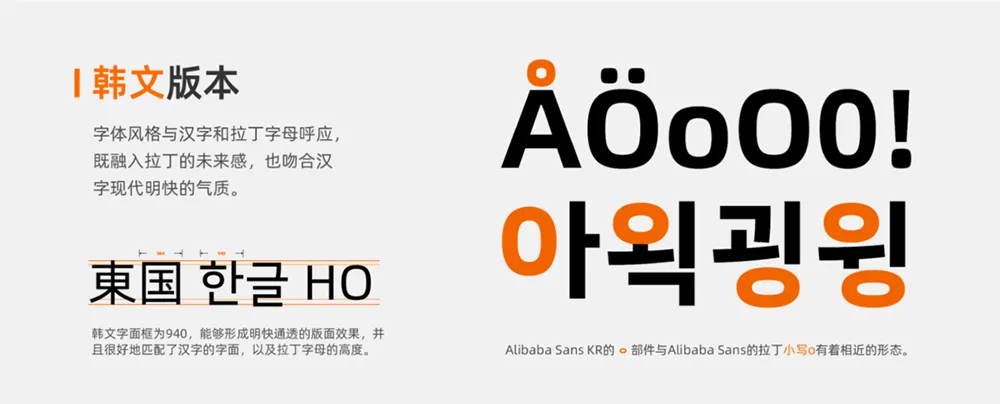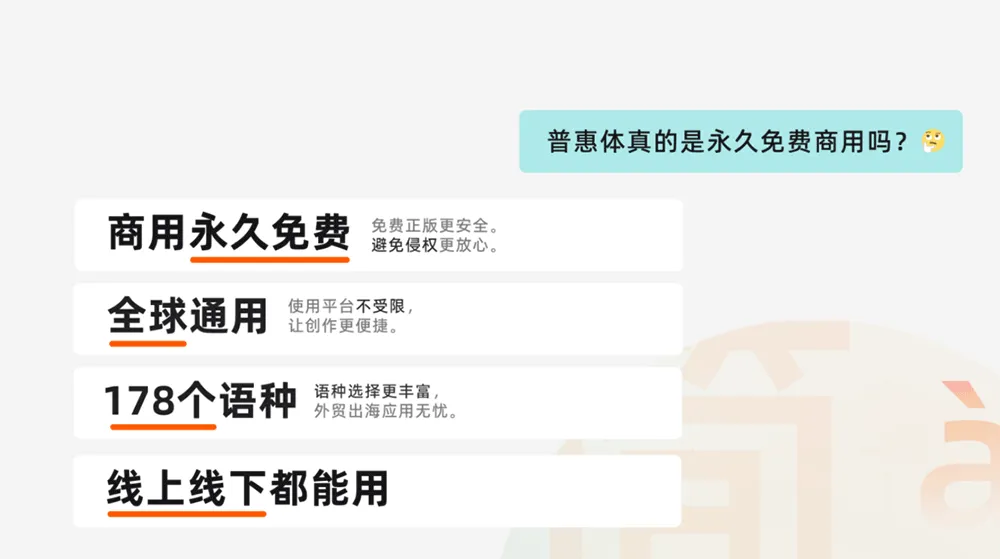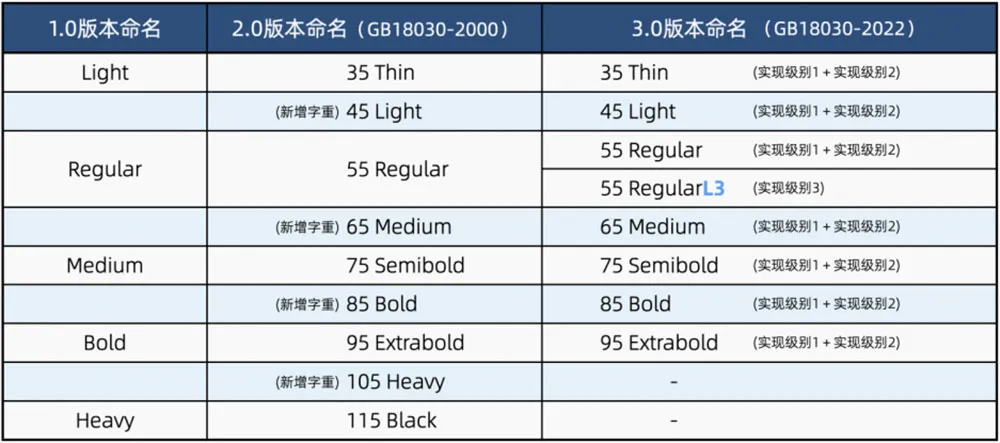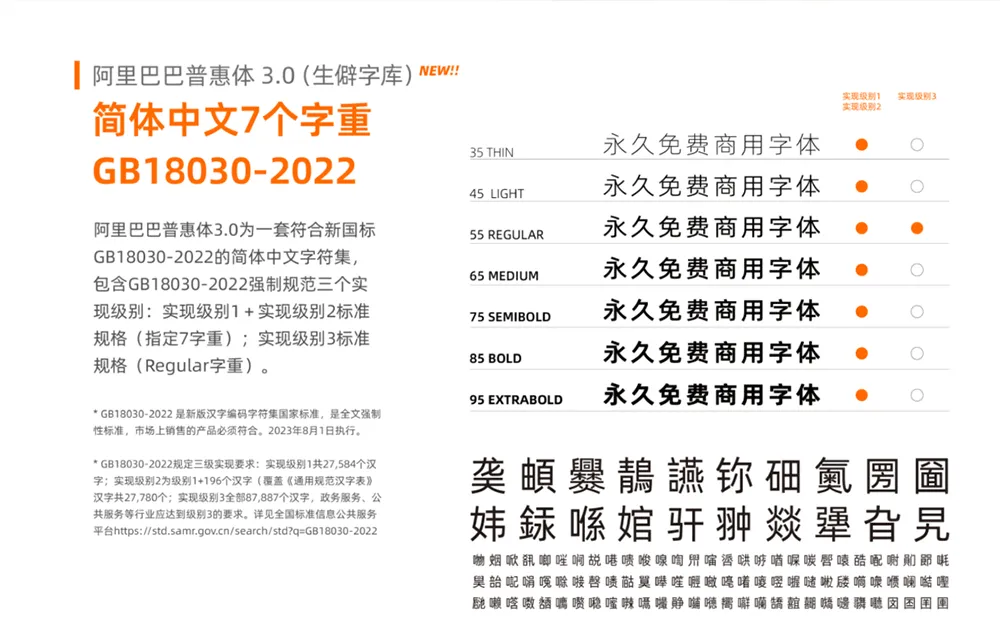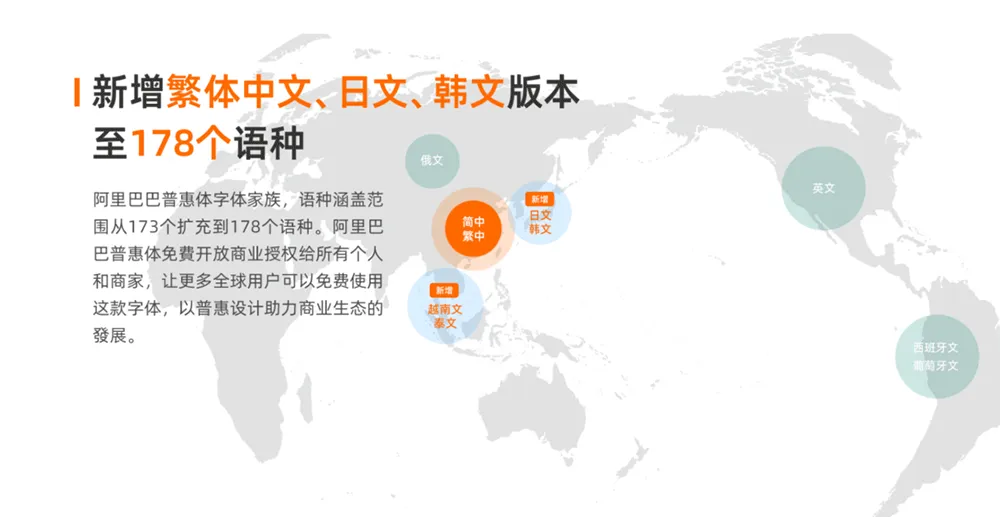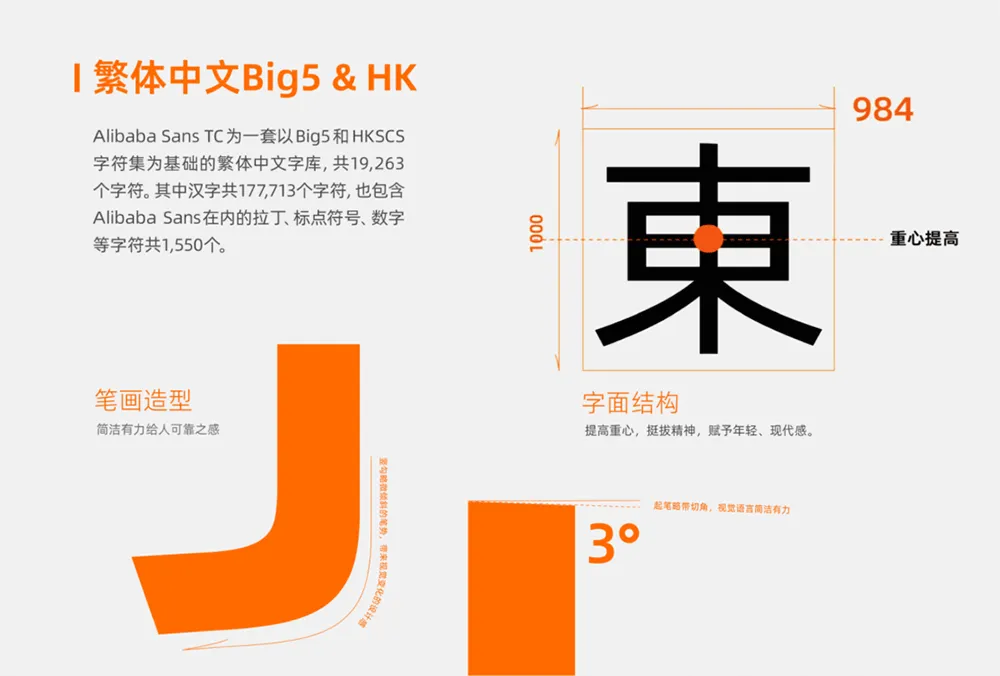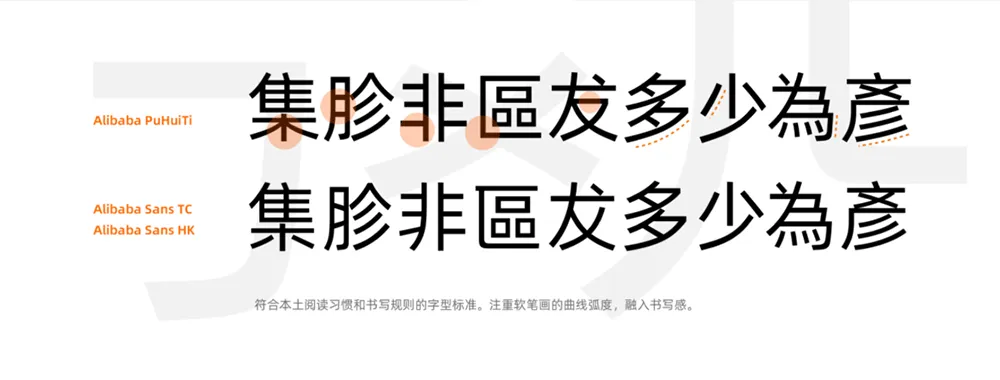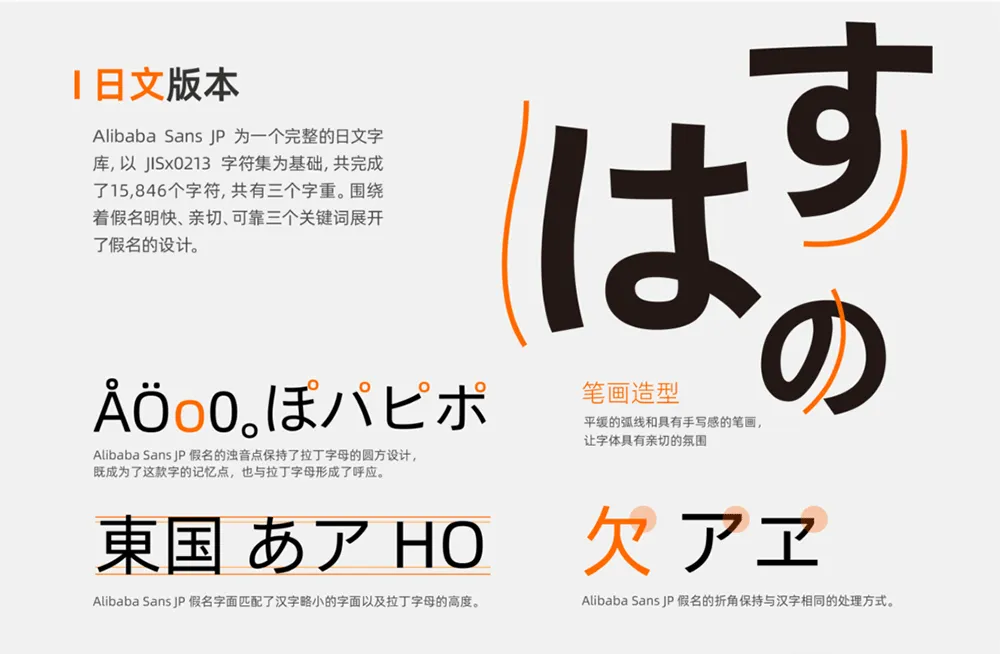
阿里巴巴普惠體是一套全球永久免費正版商用的字體家族,目前涵蓋178個語種。阿里巴巴普惠體是一款由中國企業首次發佈的可面向全場景使用的免費商用正文字體。以「普惠」之名誕生,阿里巴巴普惠體開放商業授權給所有個人和商家,讓更多用戶可以免費使用這款字體,以普惠設計助力商業生態增長。
阿里巴巴普惠體3.0為一套符合新國家標準GB18030-2022的簡體中文字符集,包含GB18030-2022強制規範三個實現級別:實現級別1+實現級別2標準規格的7字重、實現級別3標準規格的Regular 單一字重。7字重共194,460個全形漢字。包含拉丁字母、希臘字母、西裡爾字母、標點符號。
甚麼是GB18030-2022版本?阿里巴巴普惠體3.0(GB18030-2022版本)對比普惠體2.0有哪些不一樣?
1. 阿⾥巴巴普惠體3.0版,在2.0版的基礎上,新增拓展了符合國標GB18030-2022規格的簡體中文字庫(指定7款字重)。現有簡體中文(指定9款字重)、越南文和泰文字體(指定3款字重)、韓文字體(指定3款字重)、日文字體(指定3款字重)、繁體中文(Big5和HK分別指定4款字重),前述字體及包含該字體的字庫軟件,合稱 “阿⾥巴巴字體”。